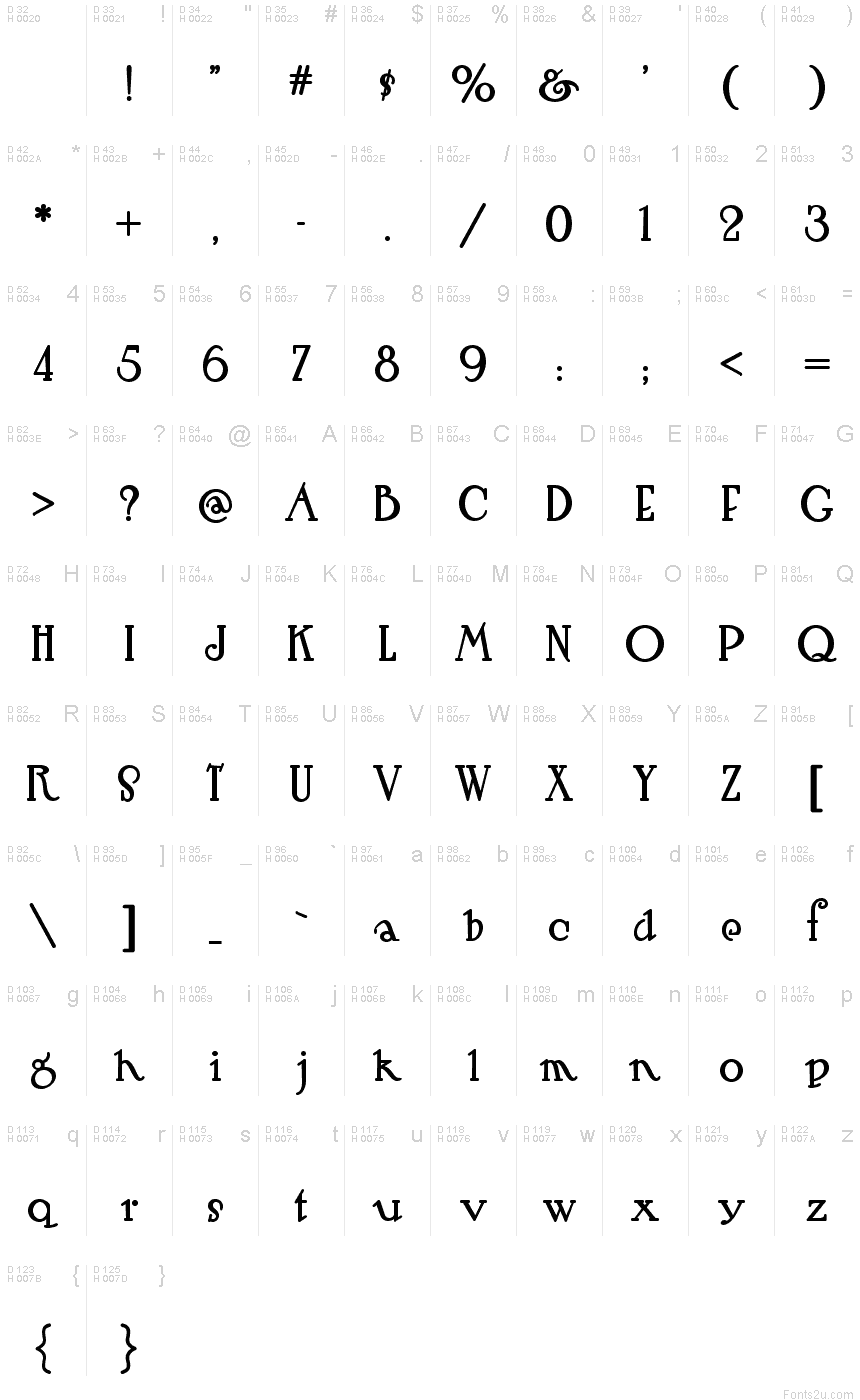
Hut Sut Ralston NF autorstwa Nicka Curtisa to bezpłatny, retro krój szeryfowy typu display, nawiązujący do swobodnego stylu liternictwa widowiskowego z początku XX wieku. Wyraziste kontrasty grubości kresek, zawinięte podstawy szeryfów i asymetrycznie wyważone kształty liter nadają mu teatralną sylwetkę – jakby każdy znak został narysowany ręcznie na afisz wodewilowy.
Najlepiej sprawdza się na plakatach, zwłaszcza w zapowiedziach wieczorów kabaretowych, występów komediowych czy imprez w klimacie vintage. Pasuje również do pomysłowych opakowań oraz szyldów restauracyjnych, gdzie przerysowane łuki wnoszą urok minionej epoki bez potrzeby sięgania po bogate zdobienia. Zamiast pełnić funkcję neutralnego tekstu, liternictwo to świetnie odnajdzie się jako element ilustrowanej markizy teatralnej lub szyldu sklepowego.
Hut Sut Ralston NF